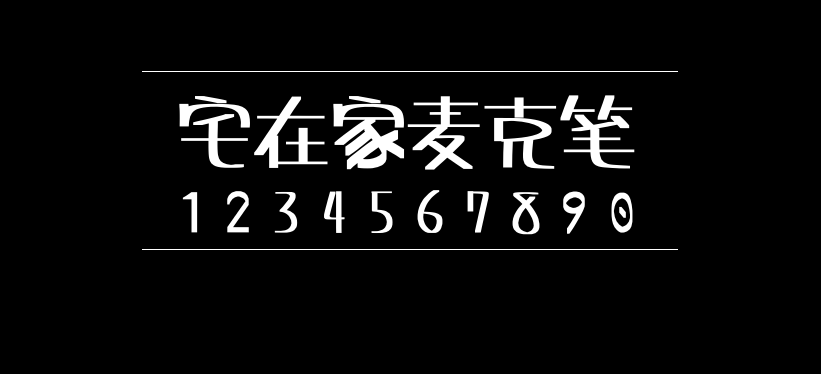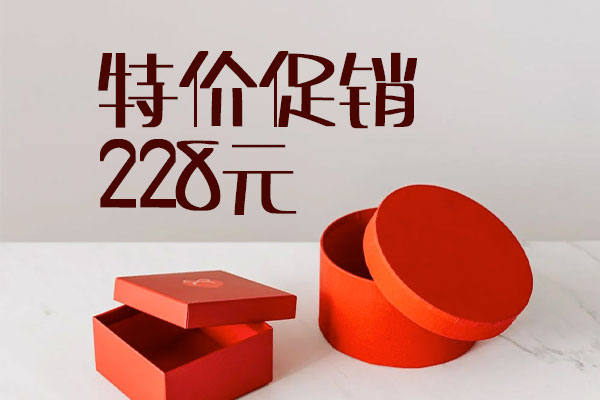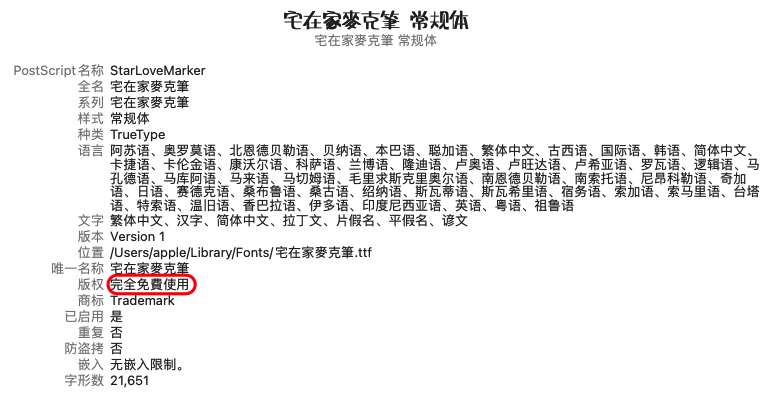
宅在家麦克笔
宅在家麦克笔(StarLoveMarker)是中国台湾网友“天天宅在家”创作的一款手写马克笔风格字体,作者声明宅在家麦克笔为免费商用字体,所有人皆可自由下载使用。亦可随意改作与再发布,不限于任何用途。宅在家麦克笔字体的字体文件属性中也可以看到注明“完全免费使用”。
宅在家麦克笔的简体和繁体支持得都比较好,已覆盖简体国标GB2312的6763字,基本不存在缺字现象。
宅在家麦克笔